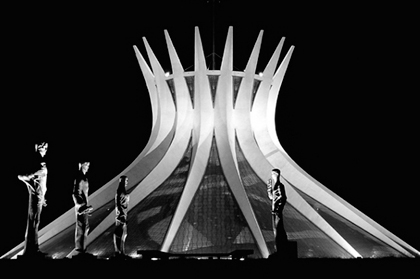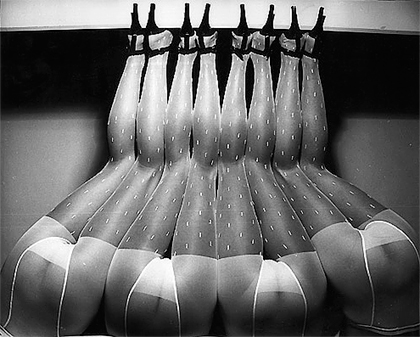
Guy Bourdin ou le pied de la Lettre
Parfois je me demande s’il faut toujours écrire qq chose, bien que la légende soit des plus nécessaires, mais ici sur cette photo —comme disait Barthes, “une photo sans légende, est saturée de sens”.— on pourrait donc délirer pendant des heures. Quand je l’ai vu par exemple j’ai immédiatement pensé à le typo, aux pleins et déliés, au corps, à l’épaisseur light d’une Dax FF, et surtout à des approches très serrées… Sex spacing typography, disait Hermann Zapf. J’ai enfin trouvé la parfaite illustration de son propos. D’autres photos de Guy Bourdin et également des images d’une grande intensité érotique via ponyExpress… Et vous? ça vous fait penser à quoi?
Christian et Soheil se sont mis d’accord sur la cathédrale de Notre Dame de l’Apparition réalisée par l’architecte Oscar Niemeyer, à Brasilia. Bien vu:-)
Notre Dame de l’Apparition ! Bien vu Soheil ! :-)
(Niemeyer trop fort, j’ai eu droit un jour à un compte-rendu d’entretien de Le Corbusier avec le grand Oscar, à se tordre de rire…)